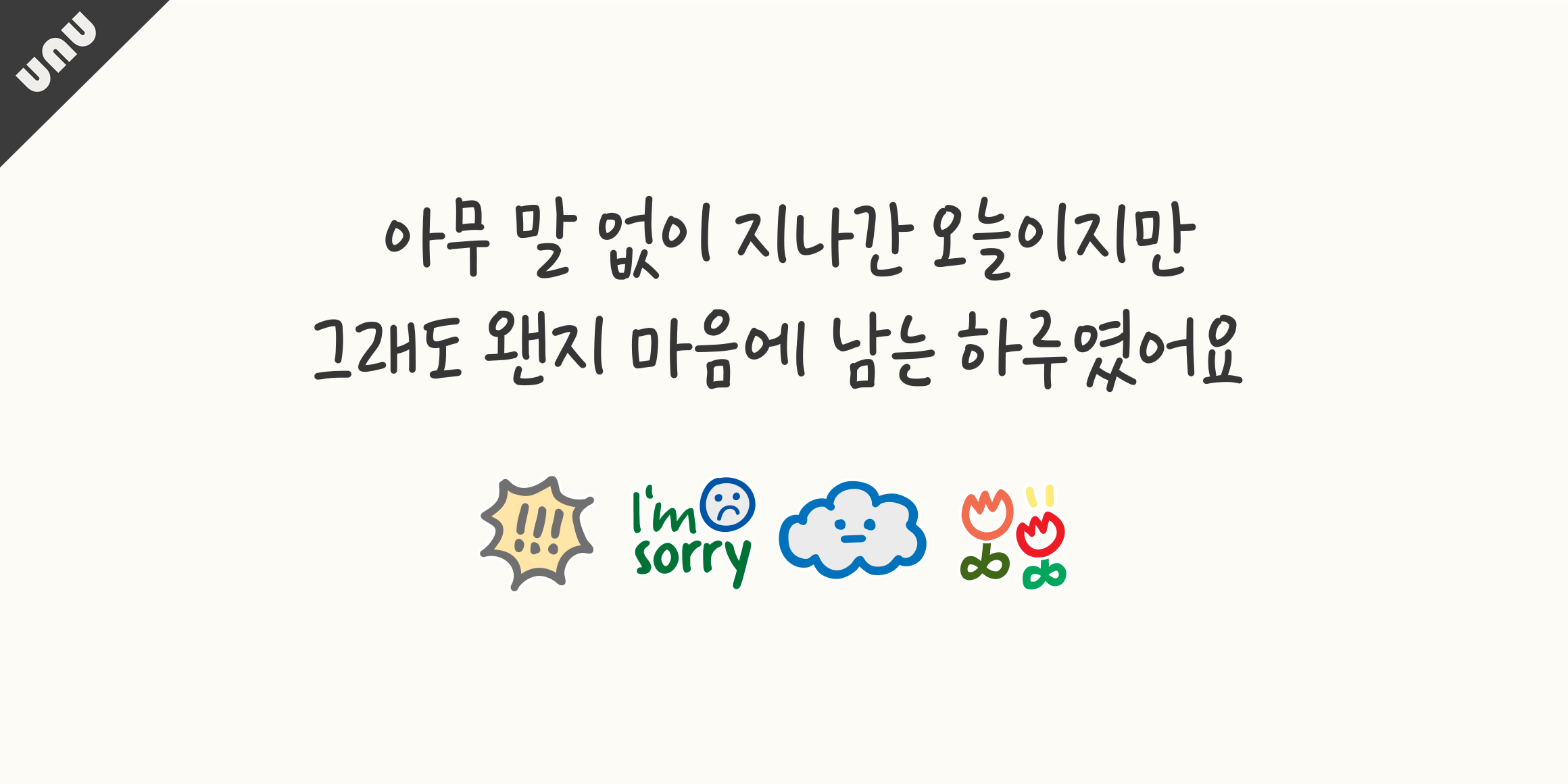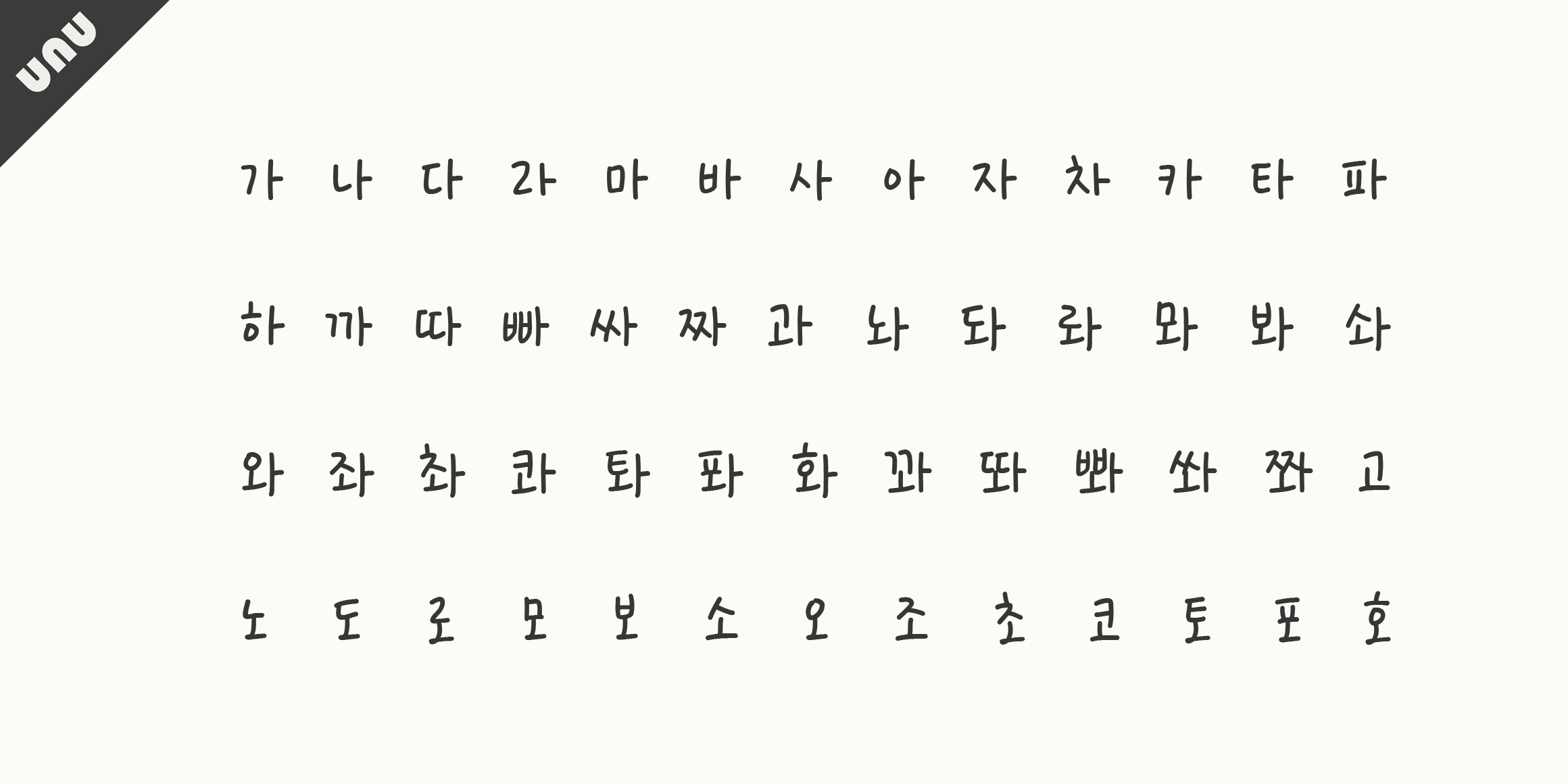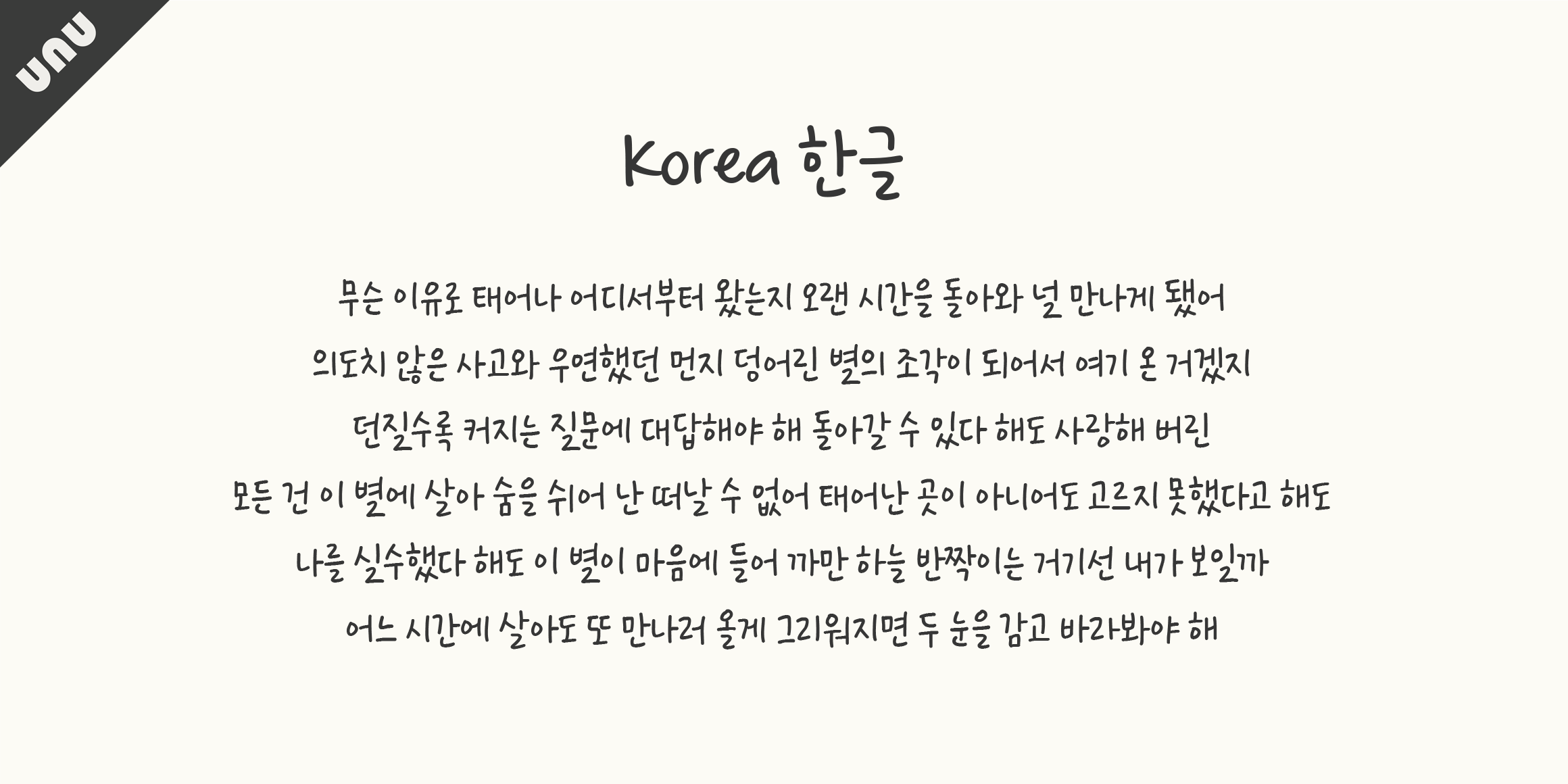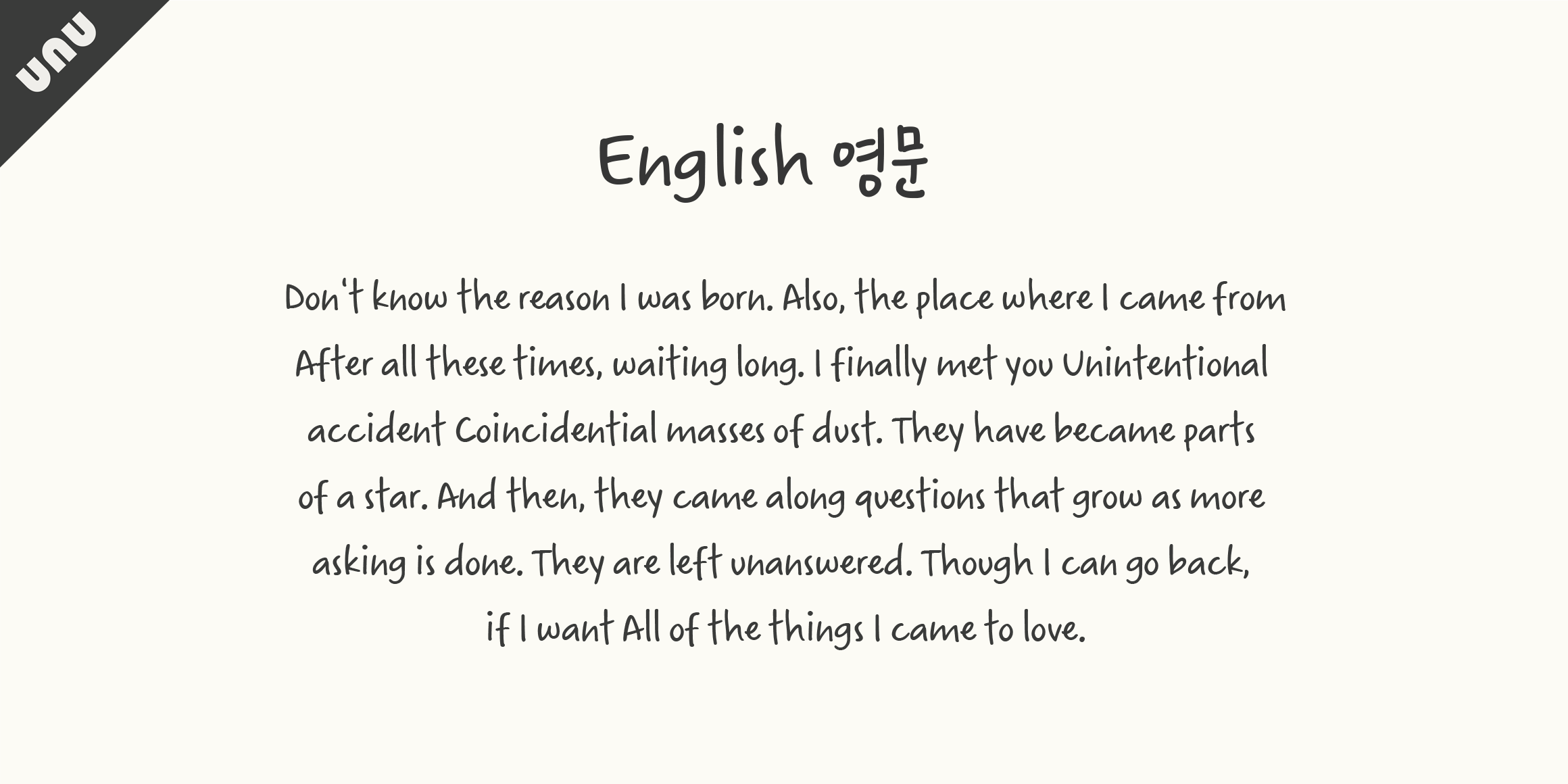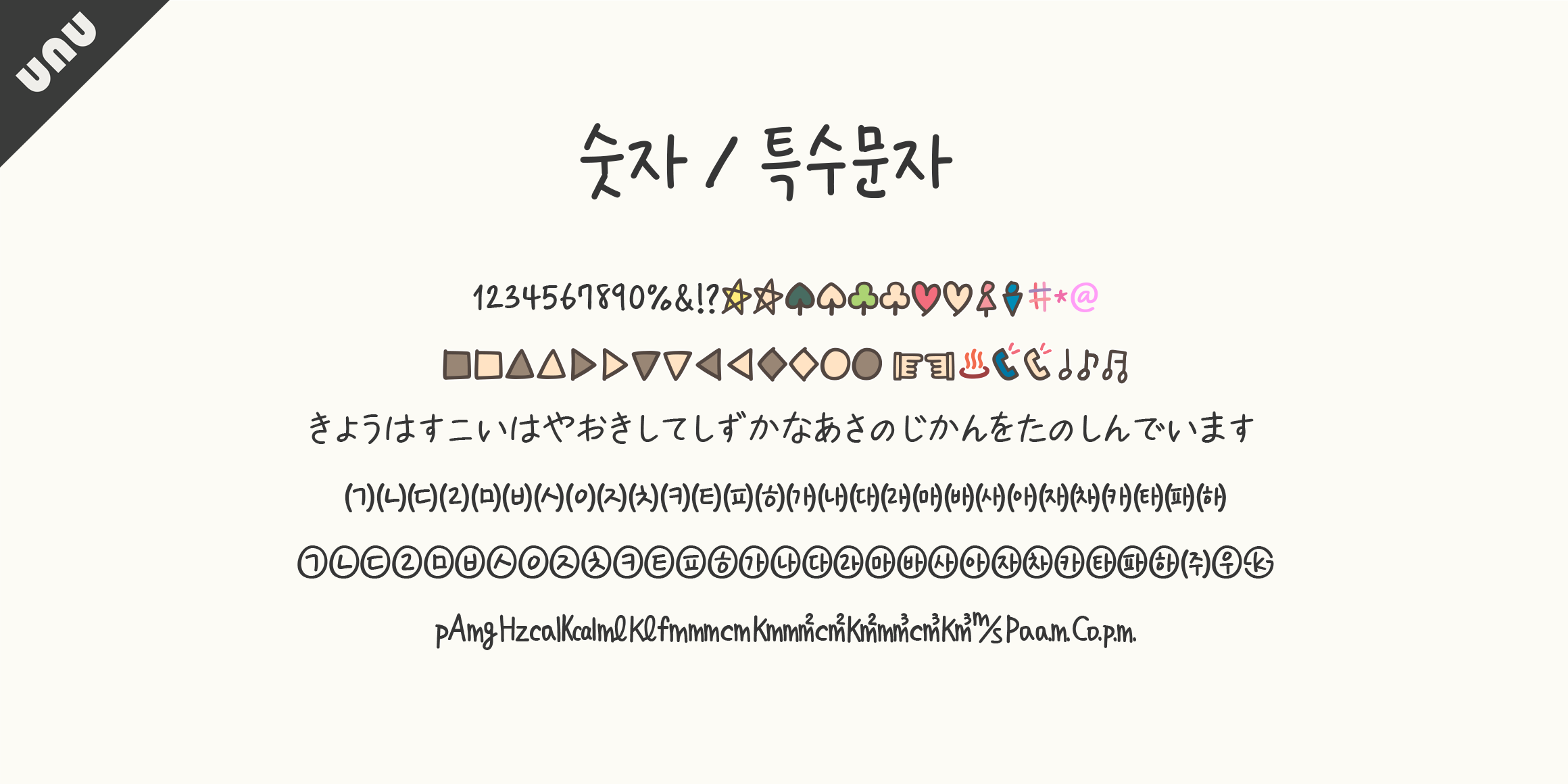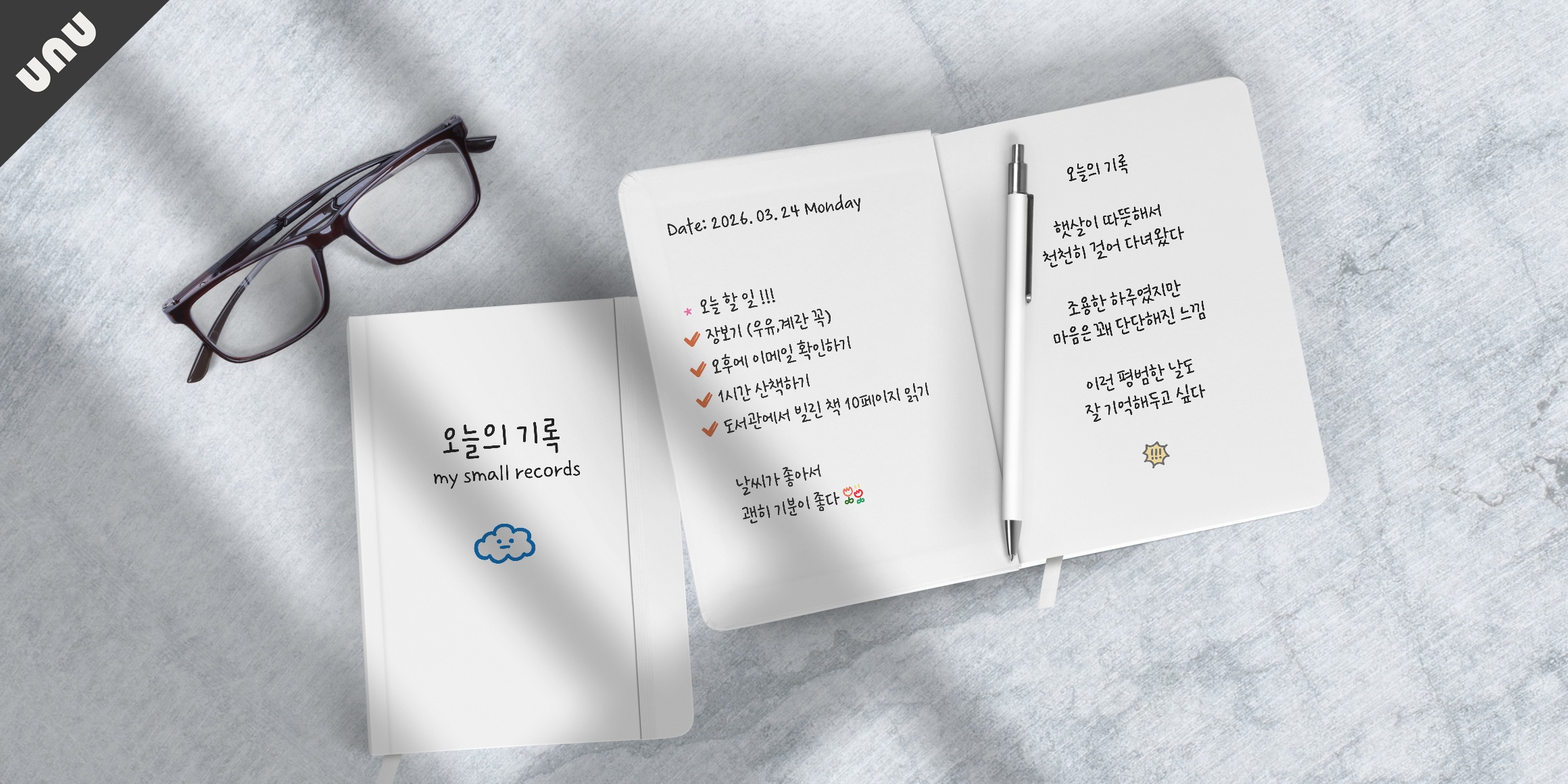
unu너에게편지를써
분류 Script,손글씨
unu너에게편지를써 font in use
이 서체는 자연스러운 필기스타일이 살아 있는 매력적인 손글씨입니다. 사랑하는 누군가에게 따뜻한 마음을 전하고 싶을때, 내 소중한 다이어리에 오늘을 기록하고 싶을때 추천드립니다. 유앤유서체는 당신의 따뜻한 마음을 전해드립니다.(컬러가 적용되지 않는 기기나 앱이 있을 수 있으며, 두껍게(Bold)처리시 두께 변화가 없을 수 있습니다.)
• 한글 11,172자 / 라틴 95자
• Script,손글씨
• unu너에게편지를써 / unuWritealetter